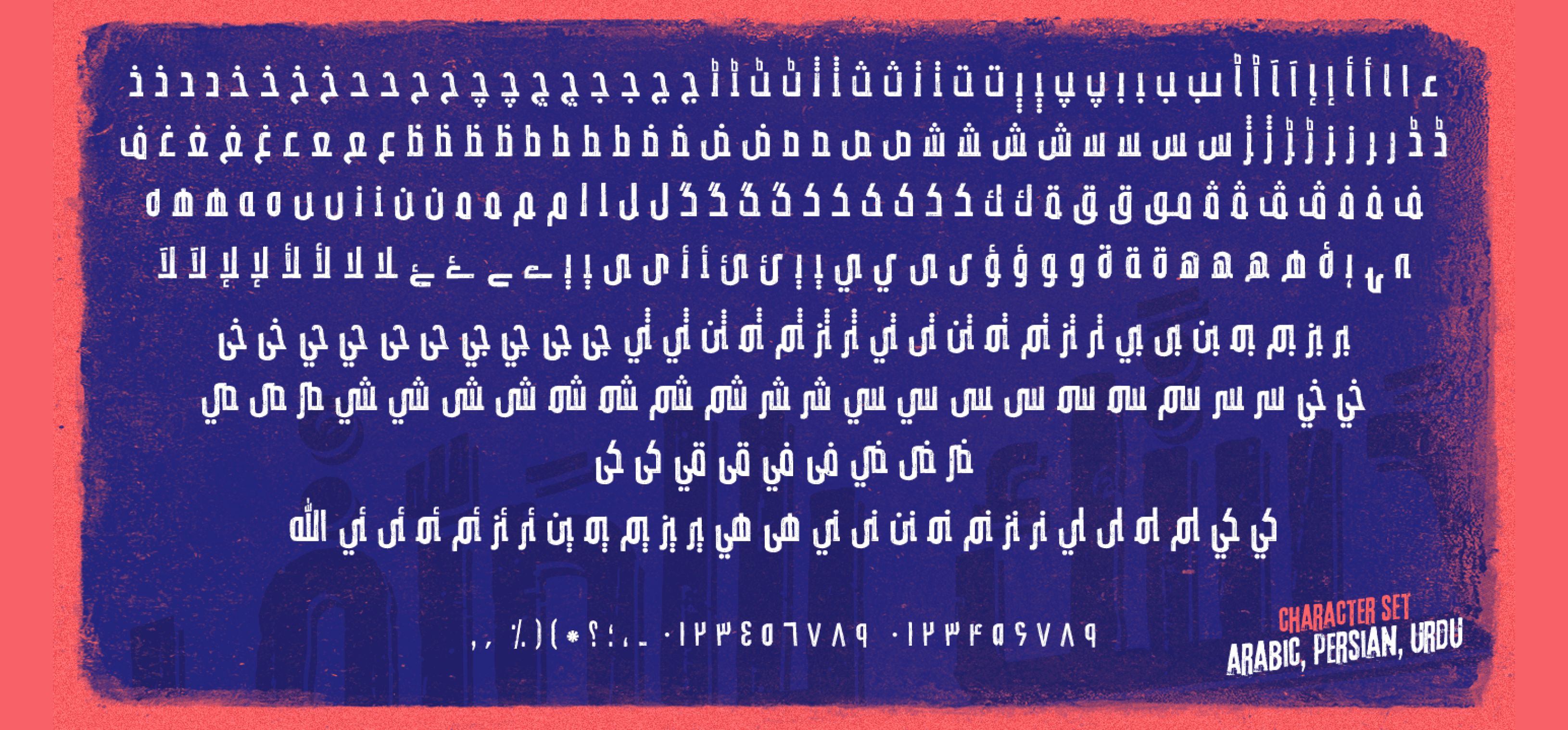
لافاه برو هو النسخة المطوّرة من الخط القديم Lava Arabic 1.0. يتميّز بأسلوب عربي ضيّق (Condensed) وخشن بلمسة متآكلة، مثالي لتصاميم البوسترات القديمة، والعلامات التجارية، والإعلانات – خاصة إعلانات الطعام أو ملصقات الأفلام.
يدعم Lavah Pro ميزات OpenType، ويحتوي على العديد من البدائل الأسلوبية (Stylistic Alternates) والربط الاختياري بين الحروف (Discretionary Ligatures).
يدعم الخط اللغات العربية والفارسية والأردية واللاتينية.